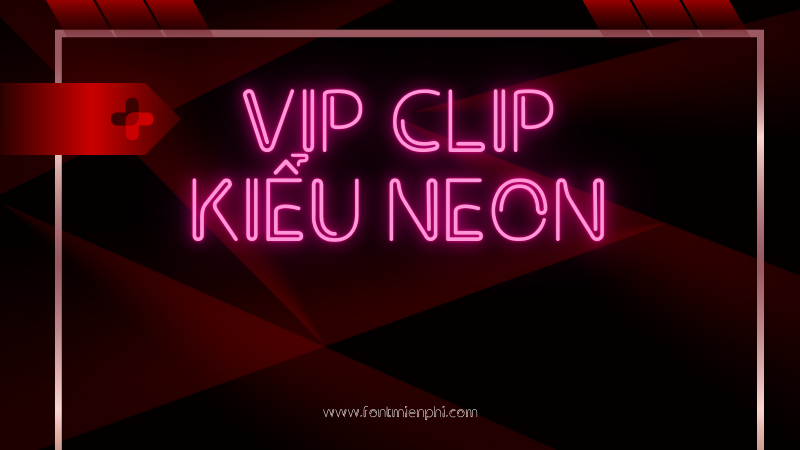
Font Việt hóa 1FTV VIP Clip – Kiểu Neon
Font Việt hóa 1FTV VIP Clip – Kiểu Neon là một kiểu chữ độc đáo, mang phong cách hiện đại và nổi bật. Đặc điểm nổi bật của font này là các đường nét sáng rực rỡ, tạo cảm giác như ánh đèn neon phát sáng.
Đặc điểm chính:
• Thiết kế hiện đại: Font được thiết kế với những đường cong mềm mại và góc cạnh sắc nét, tạo nên sự hài hòa và ấn tượng.
• Hiệu ứng ánh sáng: Các ký tự được làm nổi bật với hiệu ứng ánh sáng, giúp chúng trở nên thu hút hơn trong các thiết kế đồ họa.
• Phù hợp với nhiều mục đích: Kiểu chữ này rất thích hợp cho các dự án quảng cáo, poster, banner, hoặc bất kỳ thiết kế nào cần sự nổi bật và thu hút sự chú ý.
• Hỗ trợ tiếng Việt: Font được Việt hóa đầy đủ, đảm bảo rằng người dùng có thể sử dụng các ký tự tiếng Việt mà không gặp phải vấn đề gì.
Với những đặc điểm này, font Việt hóa 1FTV VIP Clip – Kiểu Neon là lựa chọn lý tưởng cho những ai muốn tạo ra sản phẩm thiết kế ấn tượng và bắt mắt.